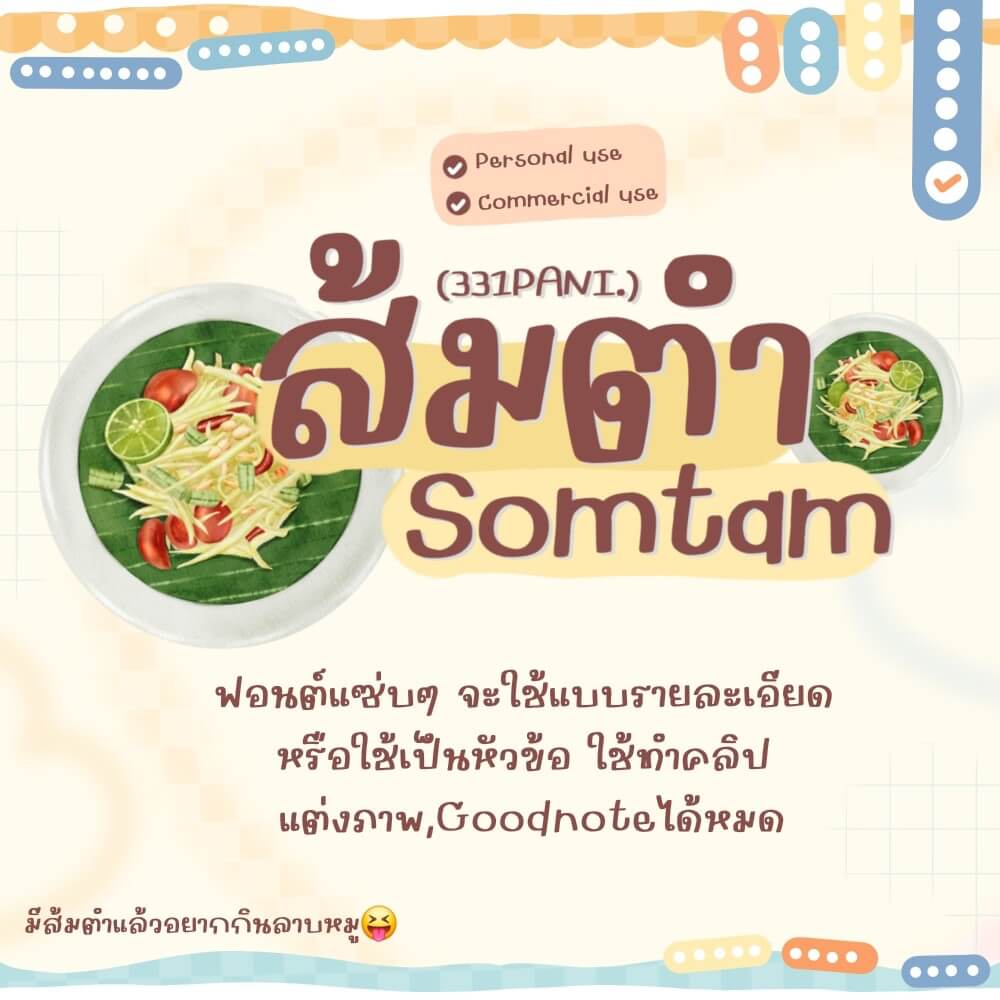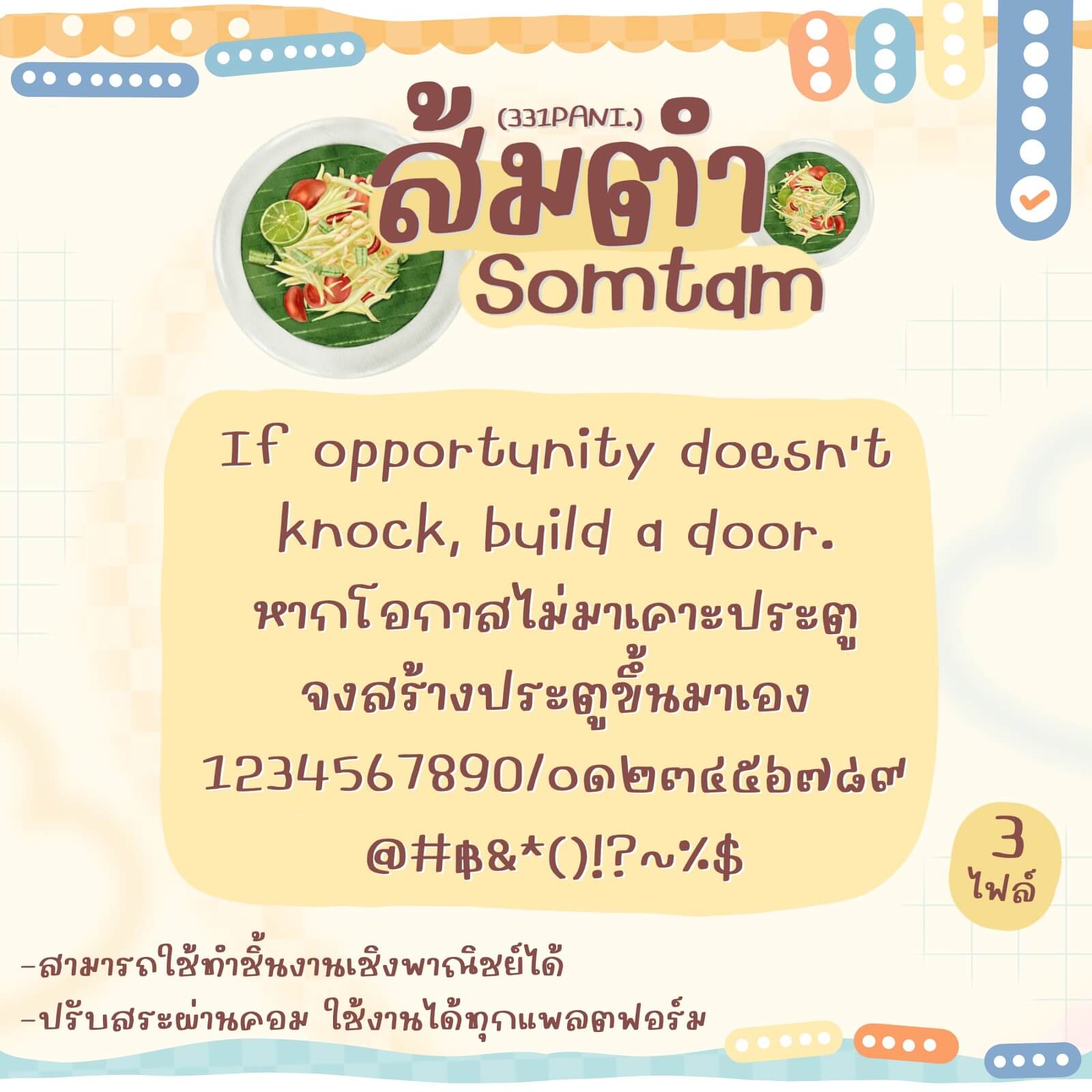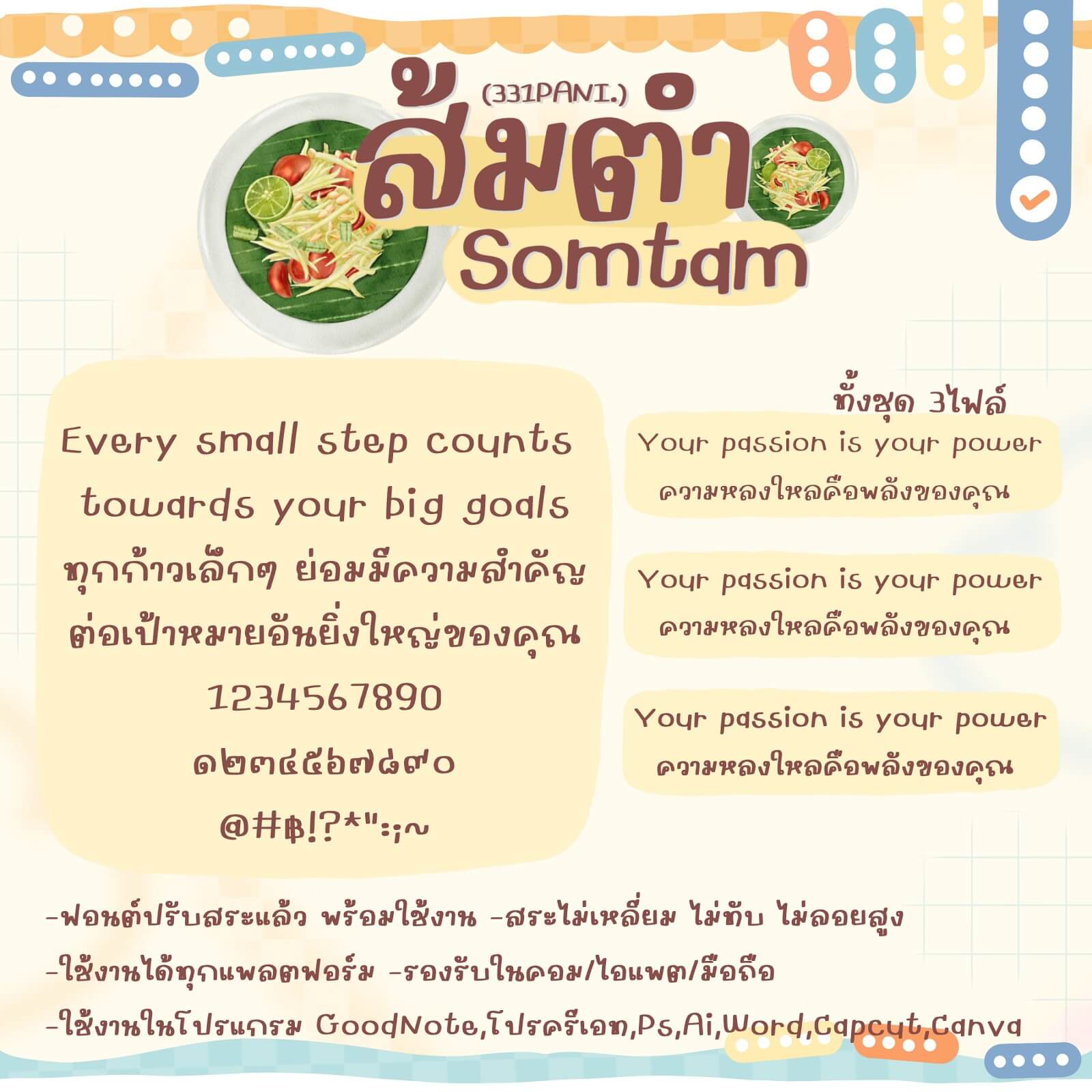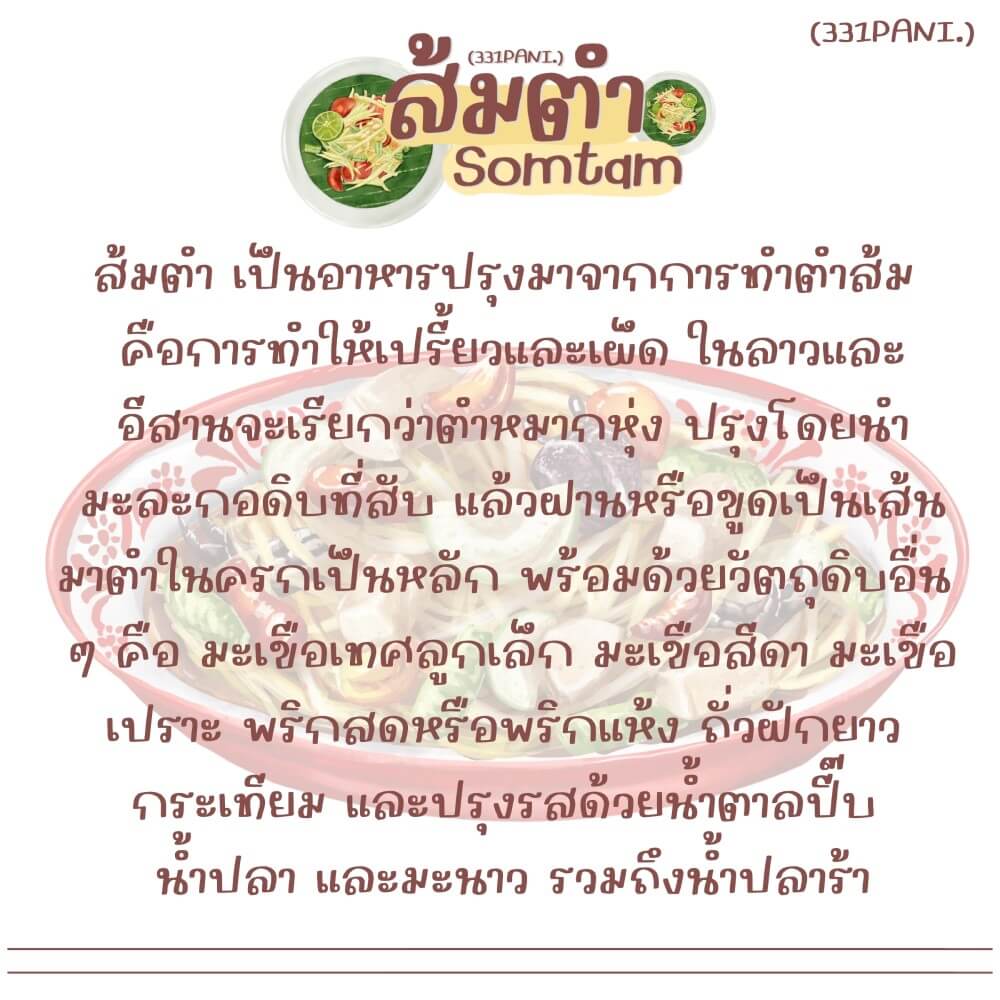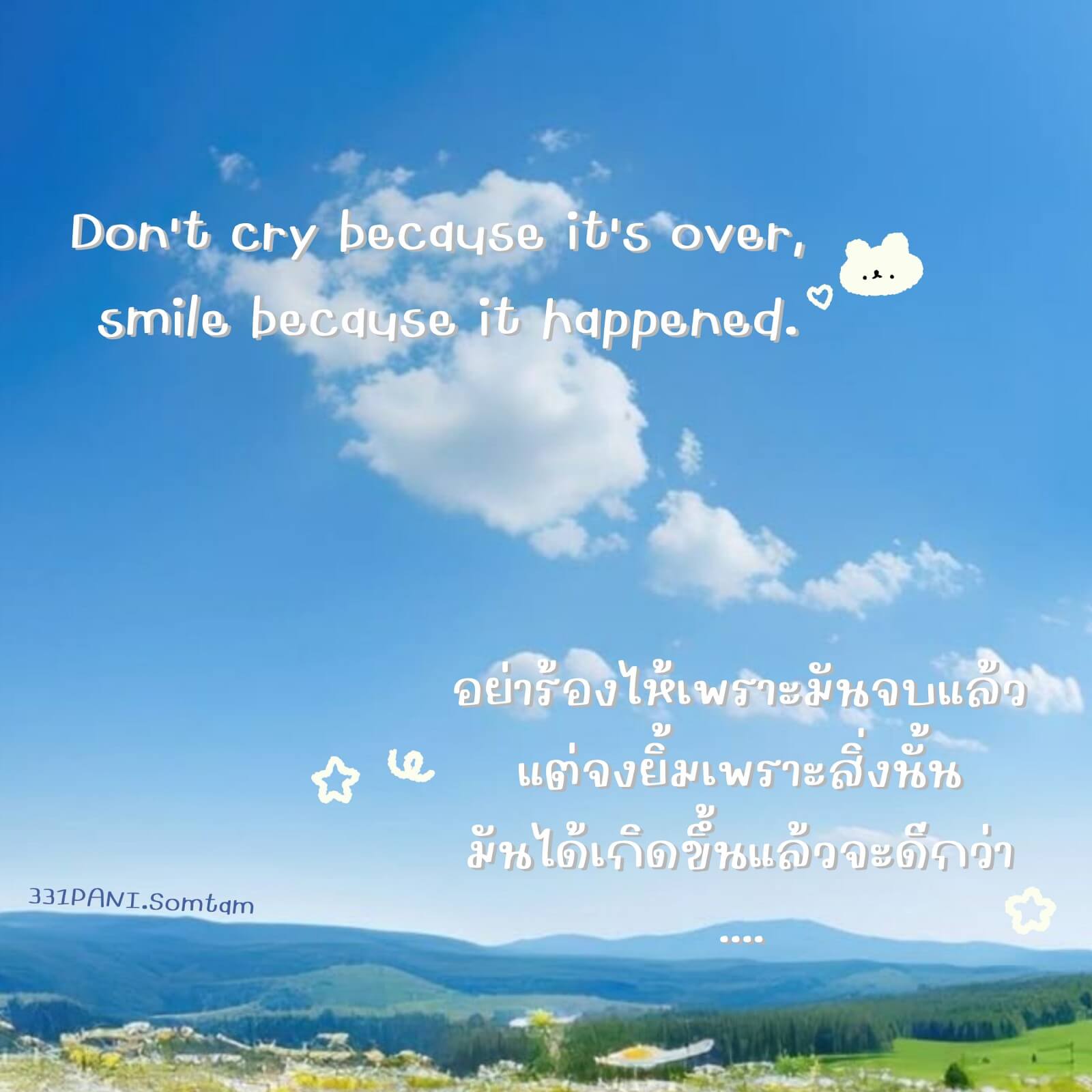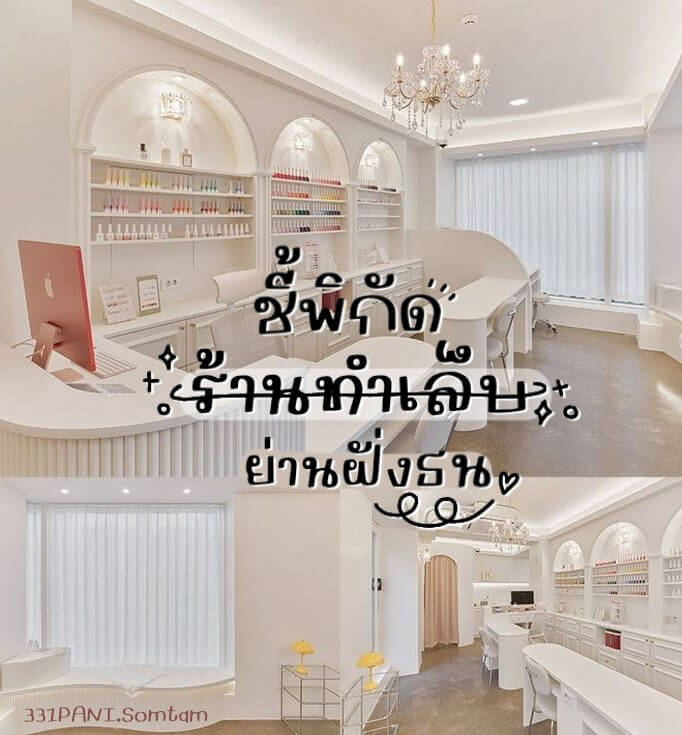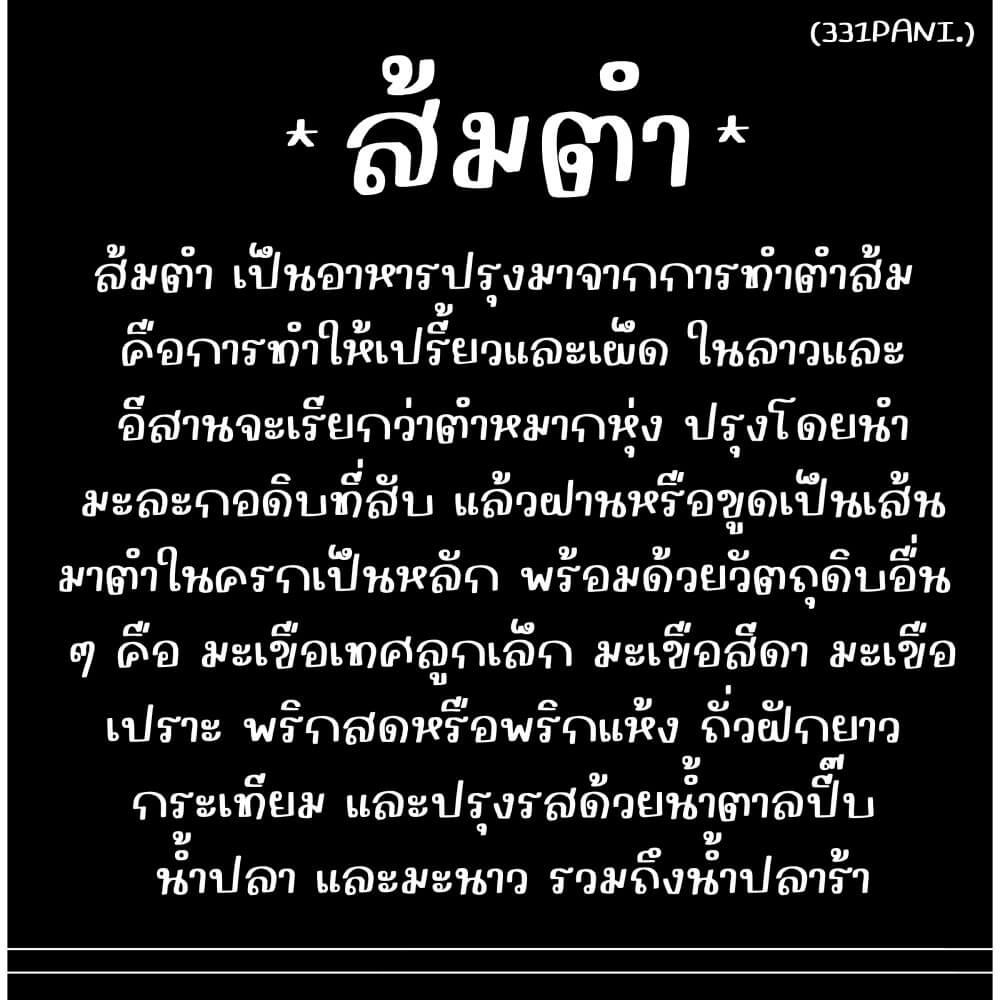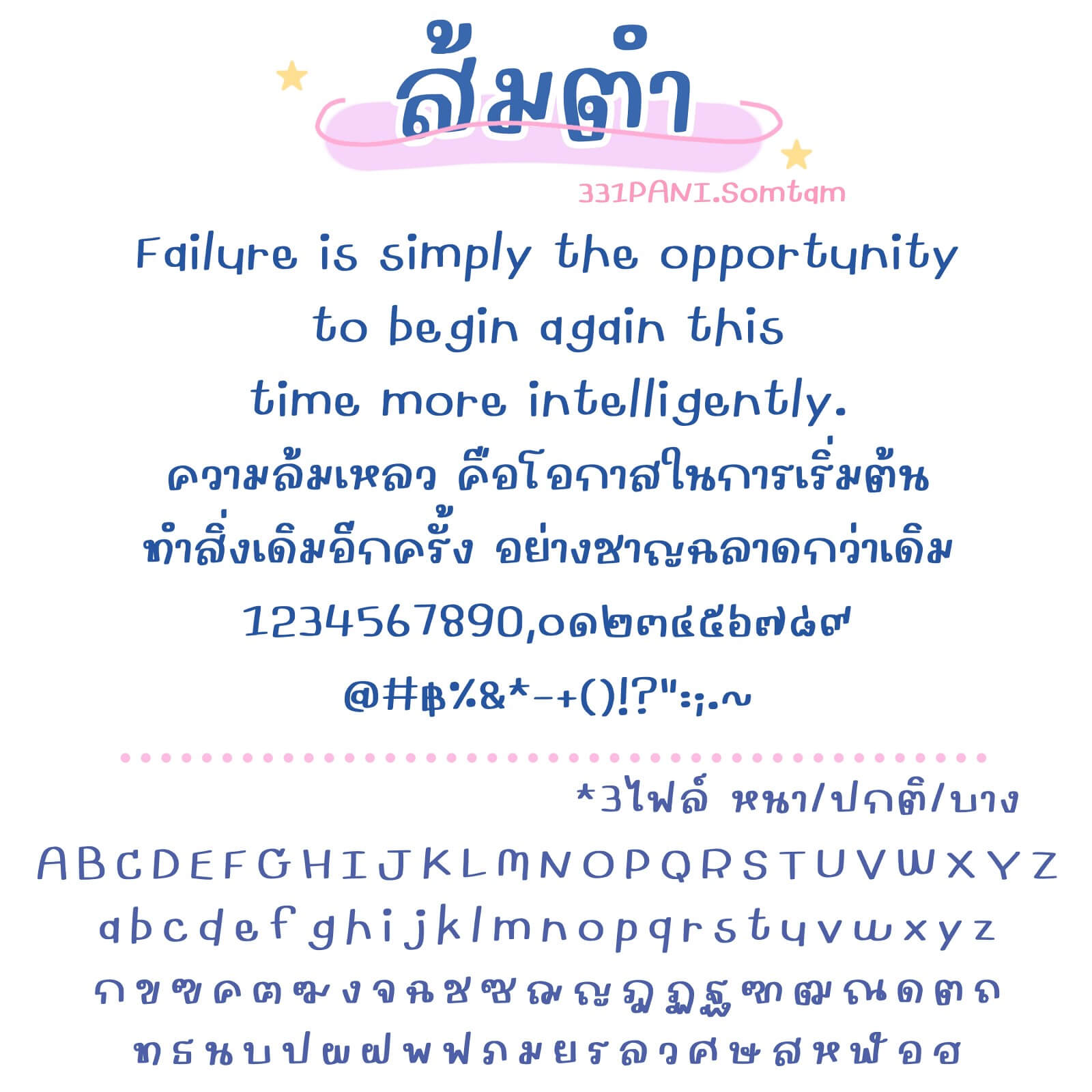
ฟอนต์ 331PANI.ส้มตำ – โหลดทดลองใช้ฟรีตัว Demo ฟอนต์แซ่บๆ จะใช้แบบรายละเอียด หรือใช้เป็นหัวข้อ ใช้ทำคลิป แต่งภาพ Goodnote ได้หมด
331PANI.ส้มตำ (331PANISomtam)